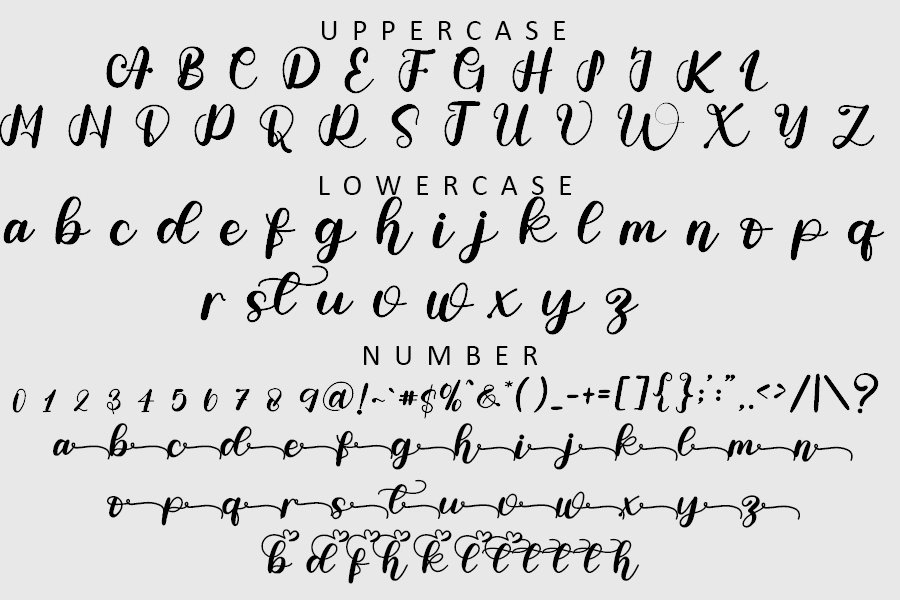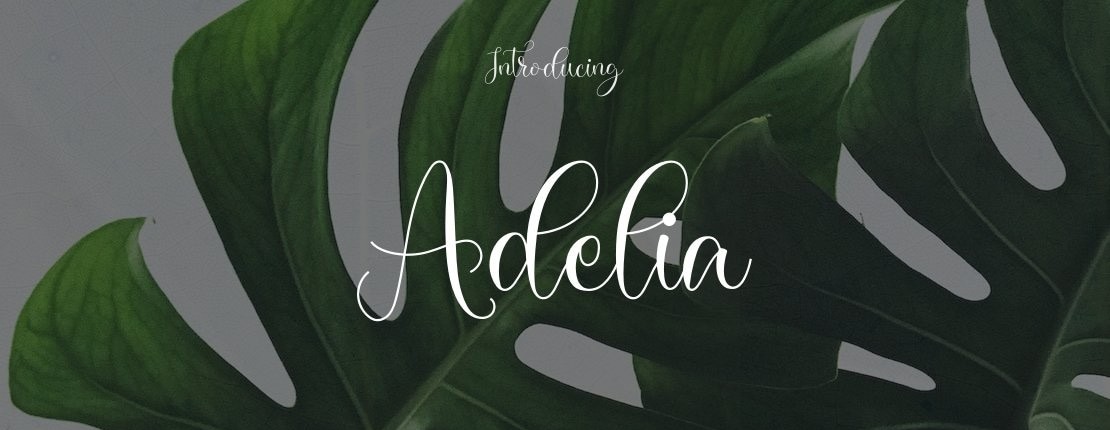
Adelia font là gì?
Adelia là một phông chữ thuộc dòng Script mang phong cách vô cùng mềm mại, lãng mạn và đầy ngẫu hứng. Đặc trưng của Adelia là những đường nét dày dặn kết hợp cùng các vòng xoắn nghệ thuật điệu đà, tạo cảm giác thư thái và bay bổng như nét vẽ tay của những nghệ nhân thư pháp hiện đại. Đây là phông chữ hoàn hảo cho các thiết kế logo tiệm bánh, bao bì mỹ phẩm organic, hũ mứt tết hoặc các mẫu hộp sản phẩm tri ân phái đẹp.
Vẻ đẹp của Adelia nằm ở sự tự nhiên và phóng khoáng trong từng nét nối. Bản download font Việt hóa Adelia tại In Viva đã được căn chỉnh kerning hoàn hảo, giúp các dấu tiếng Việt không bị chồng chéo lên nhau, giữ trọn vẹn tinh thần nghệ thuật của bộ chữ. Sử dụng Adelia trong thiết kế giúp món ấn phẩm cho doanh nghiệp của bạn mang đậm phong cách nhẹ nhàng và tinh tế, dễ dàng chạm đến trái tim người nhận quà.
Lưu ý: Font Adelia có cấu trúc chữ uốn lượn bay bổng. Khi in trên chất liệu vải túi canvas, bạn nên nhắc thợ in kiểm tra lưới in để mực không bị loang làm mất đi các nét trang trí điệu đà.
Ứng dụng Adelia font Việt hóa trong thiết kế in ấn
Vẻ thanh thoát của Adelia giúp các ấn phẩm trở nên độc đáo và giàu cảm xúc hơn bao giờ hết:
- Thiết kế bao bì bánh mứt và đặc sản: Chữ Adelia in trên nhãn dán decal tạo phong cách tối giản và chân thành cho sản phẩm nông sản sạch cao cấp.
- Sản xuất hộp sinh nhật cho đối tác: Những lời chúc viết bằng font Adelia giúp ấn phẩm tri ân trở nên ấm áp và mang đậm dấu ấn cá nhân của thương hiệu.
- In logo lên bộ ấm chén sứ: Hình ảnh chữ nghệ thuật dùng font Adelia in nung trên men sứ trắng là sản phẩm cho đối ngoại vô cùng thanh nhã và bền bỉ.
- Trang trí voucher và thẻ VIP tri ân phái đẹp: Tạo sự khác biệt cho khách mời thông qua những tà chữ mềm mại sắc sảo trên chất liệu giấy mỹ thuật cao cấp.
Sử dụng font chữ Adelia cần lưu ý gì?
Để họa tiết chữ uốn lượn nghệ thuật này hiển thị đẹp trên thành phẩm thực tế, designer cần chú ý:
- Xử lý các nét chồng lấp (Ligatures): Adelia có nhiều nét nối bay bổng. Bạn nên kiểm tra kỹ các điểm giao nhau giữa các ký tự để tránh tình trạng mực bị bết khi in lụa mực cao cấp.
- Lựa chọn tông màu Pastel: Adelia cực kỳ hợp với các tông màu nhẹ nhàng như hồng phấn, xanh mint hoặc nhũ bạc, tạo không gian thiết kế lãng mạn.